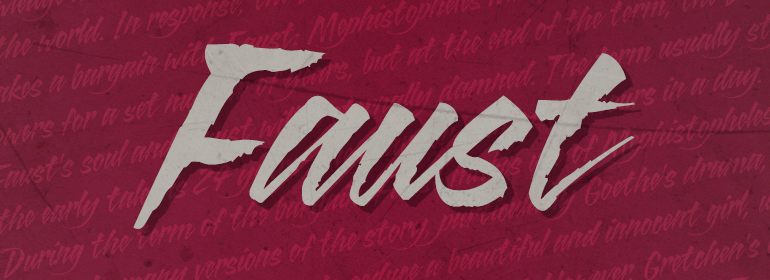
ITC Blaze™
ITC Blaze™,这款字体结构工整、笔画清晰,兼顾美观与易读性,适用于标题、正文、海报、包装、LOGO 等多种场景。字形优雅稳定,风格百搭耐看,适配日常排版与创意设计,让文字呈现更舒适、更具质感。ITC Blaze™一笔一画,皆是细节,以均衡的比例、流畅的线条打造舒适视觉体验,字形端正大气,风格简约现代。无论是商业设计、品牌宣传还是日常排版,都能轻松驾驭,让文字更有格调与力量。ITC Blaze™字体下载。
ITC Blaze是于1995年由Patty King设计的。这是一种看上去好像是在粗纸上用粗尖笔手写的字体。字符尖端以及向右倾斜都使字体有一种动态的、充满活力的感觉。Blaze展示出20世纪40年代末的影响,最适用于标题以及短至中等长度的文本。
ITC Blaze was designed by Patty King in 1995. It is a typeface which looks as though it were written by hand with a broad tipped pen on rough paper. The pointed ends of the characters and the leaning to the right give the font a dynamic, energetic feel. Blaze shows the influence of the late 1940s and is best suited for headlines and short to middle length texts.